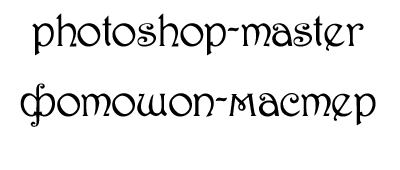
обожаю этот шрифт))
Отличный шрифит. Респект
очень красивый шрифт!
похож на сумеречный шрифт..))
Очень красивый!
красивый^^
похож на сумеречный шрифт..))
красиво)))